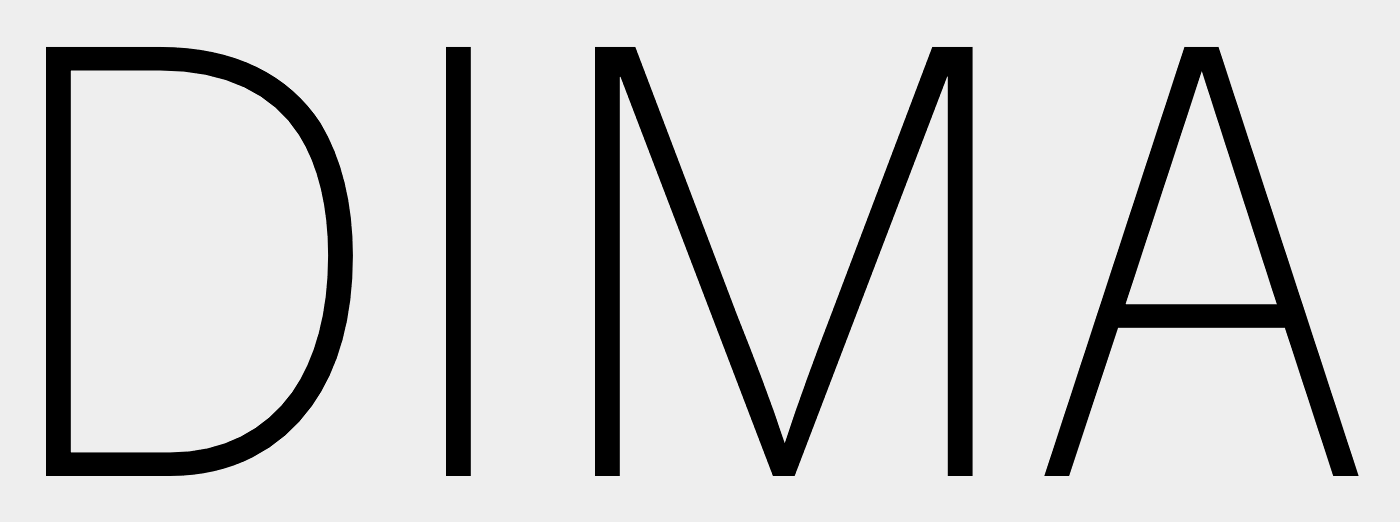
Ihr habt mir letztes Mal so großartig geholfen, danke nochmals dafür. Ich habe jetzt wieder eine Schrift, die ich suche. Kennt die jemand?
Fuller Sans wäre ähnlich, das A wurde wohl seines Balkens beraubt …
So ganz kommt sie nicht hin …
Dass das ein Lambda ist, halte ich für eher unwahrscheinlich.